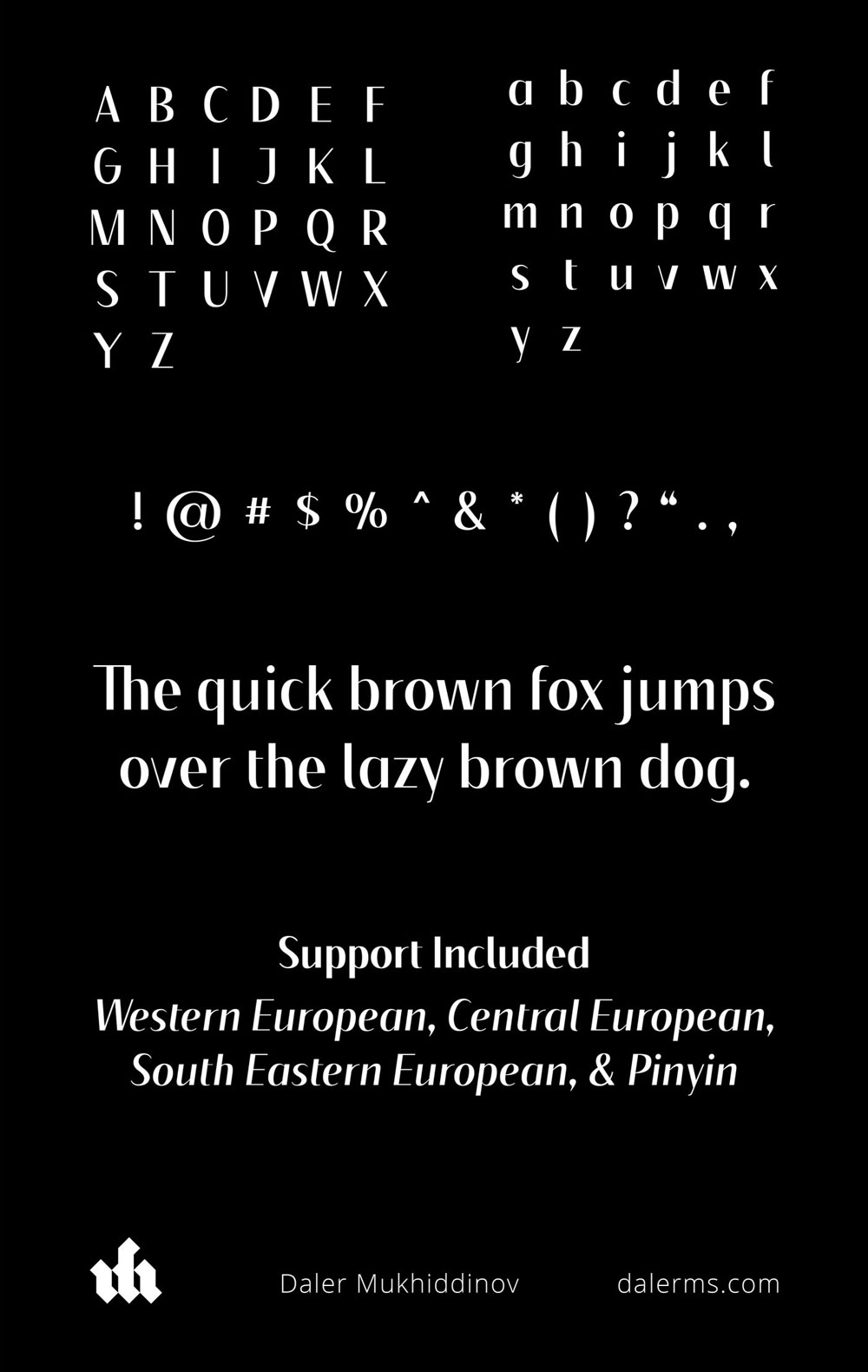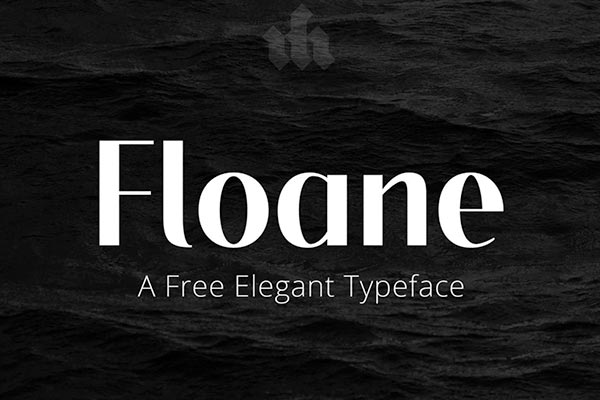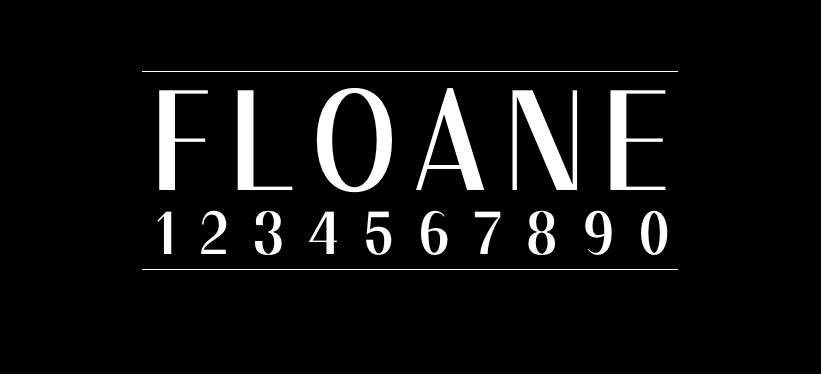
Floane
Floane字体介绍
Floane是来自美国的Daler Mukhiddinov创作的一款英文字体,100%免费。Floane字体是一种优雅的显示字体,该字体非常适合标题,文本,品牌,徽标设计,海报等。Floane有4个版本:常规,粗体,常规斜体和粗体斜体。该字体具有完整的标志符号集,并且是多语言的。
Floane字体应用示例